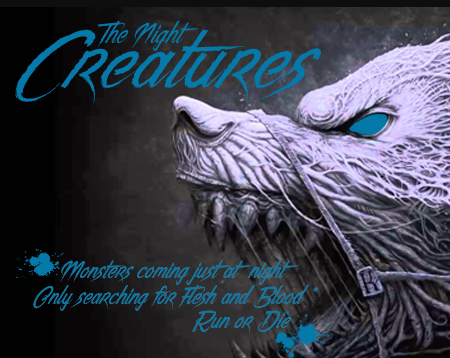
The Night Creatures Font – Download Grátis
A fonte ‘The Night Creatures Font’ é perfeita para quem busca adicionar uma nota única e criativa a suas criações digitais. Esta font foi criada pelo designer Cat Butcher, especializado em arte digital de alta qualidade. Ela combina um estilo elegante com elementos animados que remetem ao mundo da noite. Ideal para aplicar em designs como cards de aniversário, e-mails personalizados ou ilustrações originais, a font The Night Creatures é uma opção perfeita para quem deseja dar vida à sua arte digital, sem comprometer seu trabalho com conteúdo sexual. Cat Butcher permite o uso pessoal gratuito desta fonte, mas restringe o uso comercial por meio de um pedido prévio. Ela respeita as leis e as diretrizes éticas em relação ao uso das suas criações, garantindo que seus trabalhos artísticos continuem a ser uma expressão genuína da sua personalidade criativa.